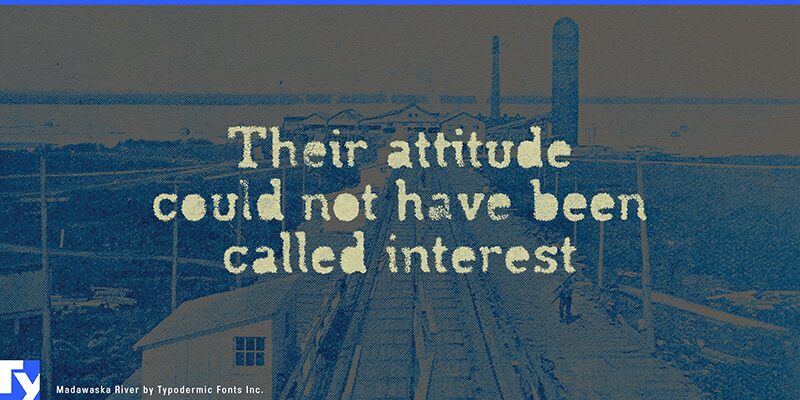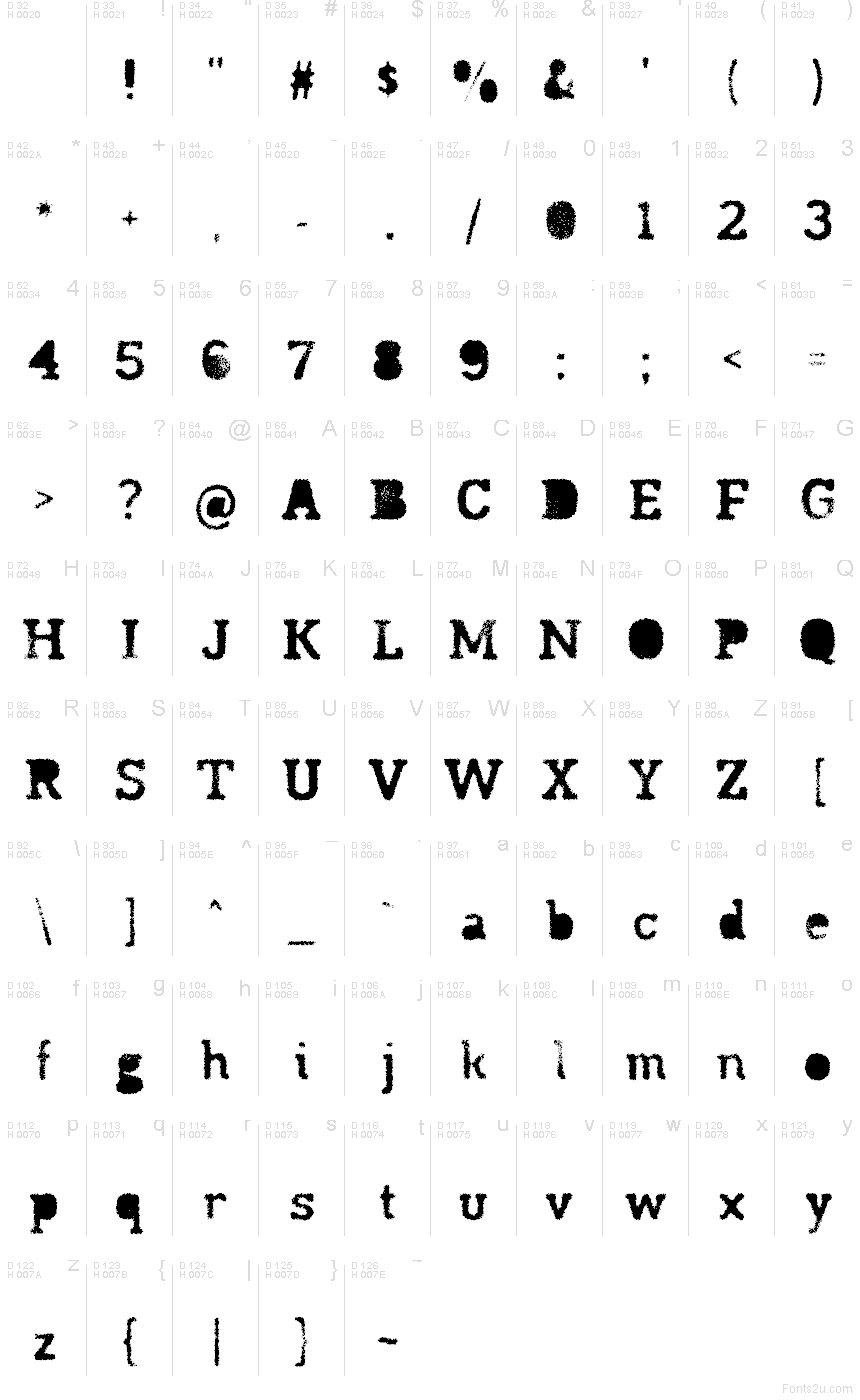
Madawaska es una tipografía egipcia (slab serif) clásica con algunas peculiaridades inesperadas que evitan que parezca una pieza de museo. Sus serifas robustas y sus proporciones relajadas le otorgan una estructura confiable, mientras que los sutiles cortes en las minúsculas aportan calidez y personalidad. Las variantes texturizadas introducen un carácter táctil y envejecido por el tiempo, lo que la hace especialmente adecuada para empaques de estilo vintage, identidad de marca con herencia tradicional, portadas de libros y diseño editorial. Con una base sólida y versátil, Madawaska reúne claridad, personalidad y un sobrio sentido de la tradición.